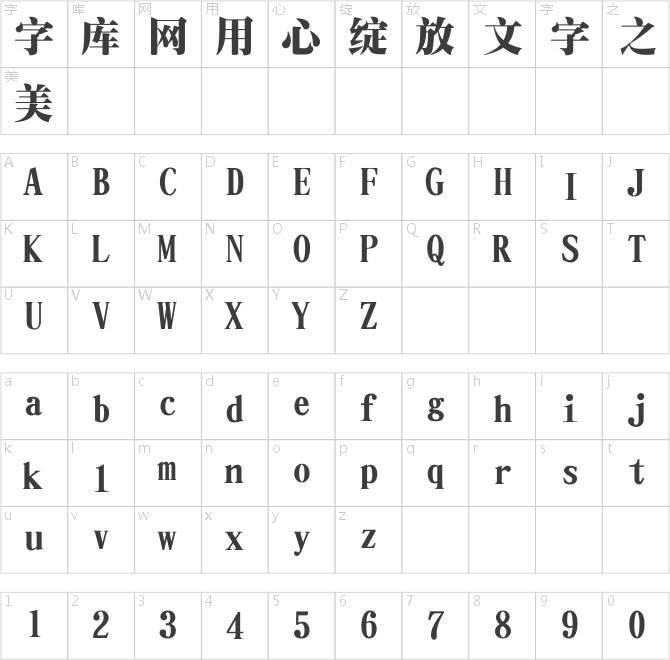
字体名称: 文鼎特粗宋简繁
文鼎特粗宋简繁
文鼎特粗宋简繁介绍
文鼎特粗宋简体big5繁体合并形成,兼容新版win10
更新Power TrueType Version 5.0版,和原Power TrueType Version 4.0或Power TrueType Version 4.5版本相比又将原Power TrueType big5的扩展471个外字集的部分没有映射字码点的汉字进行了对号入座,并修复『?』字误映射到『抝』字位置的错误。20220120更新Power TrueType Version 5.5版:添加日语当用汉字。一共16671个汉字。
文鼎特粗宋简繁字体文鼎超明简繁字库是一款让人赏心悦目、百看不厌的中文字体,适合各类广告和产品包装设计应用,字体大小12.93MB,格式为ttf字体,上传用户是伊宁,作者/版权方为文鼎字库